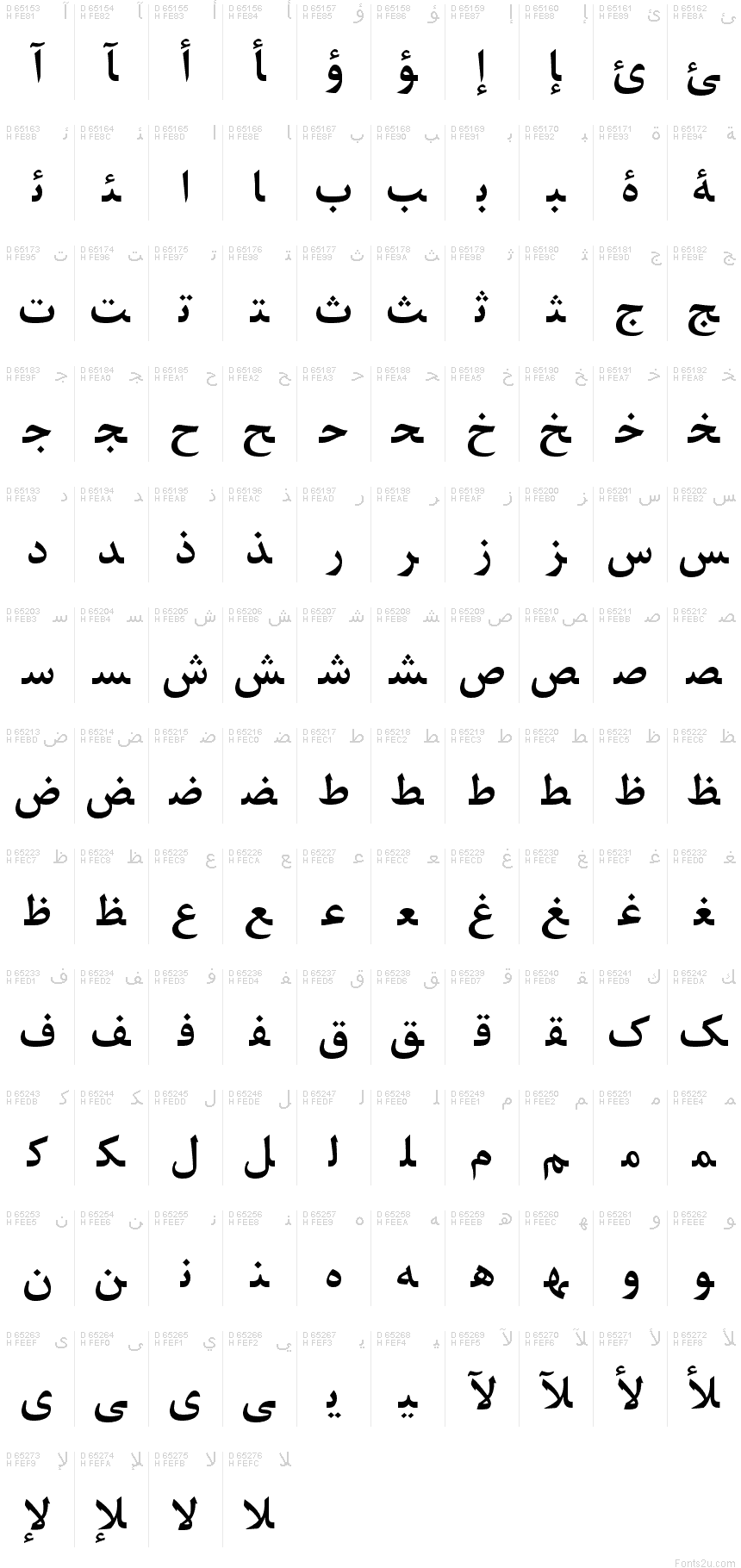
B Nazanin Bold di Borna Rayaneh è un font arabo gratuito dal tono familiare e letterario. Il design delle lettere affonda le radici nella tradizione editoriale persiana e araba: grazie ai tratti fluidi e connessi, al movimento arrotondato e al peso visivo solido, conferisce ai titoli e alle righe brevi una presenza composta e autorevole.
È perfetto per layout editoriali, poster culturali, copertine di libri, packaging e titoli di interfacce in cui si cerca una tipografia araba che comunichi solidità anziché decorazione. Essendo un font gratuito, è ideale anche per cartelli, citazioni e progetti di branding, poiché le lettere conservano un ritmo calligrafico calmo, senza scivolare nell'ornamento.